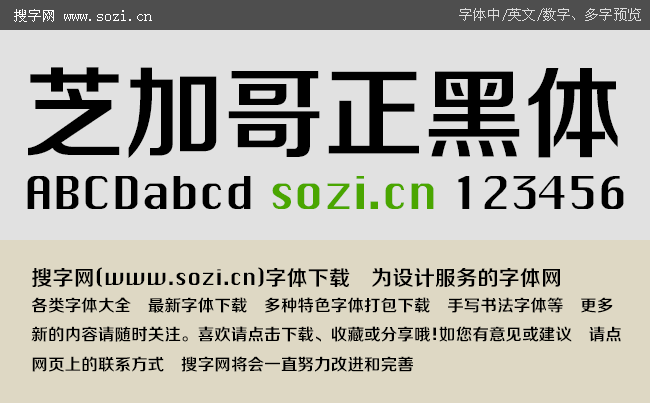
芝加哥正黑體
搜字網(wǎng)提供一款芝加哥正黑體中文藝術(shù)字體下載,芝加哥正黑體是一款中文藝術(shù)黑體字體,該字體端莊大方、品質(zhì)精良,整體效果非常出色?梢詰(yīng)用于廣告設(shè)計(jì)、平面設(shè)計(jì)、產(chǎn)品包裝、報(bào)刊雜志等領(lǐng)域。